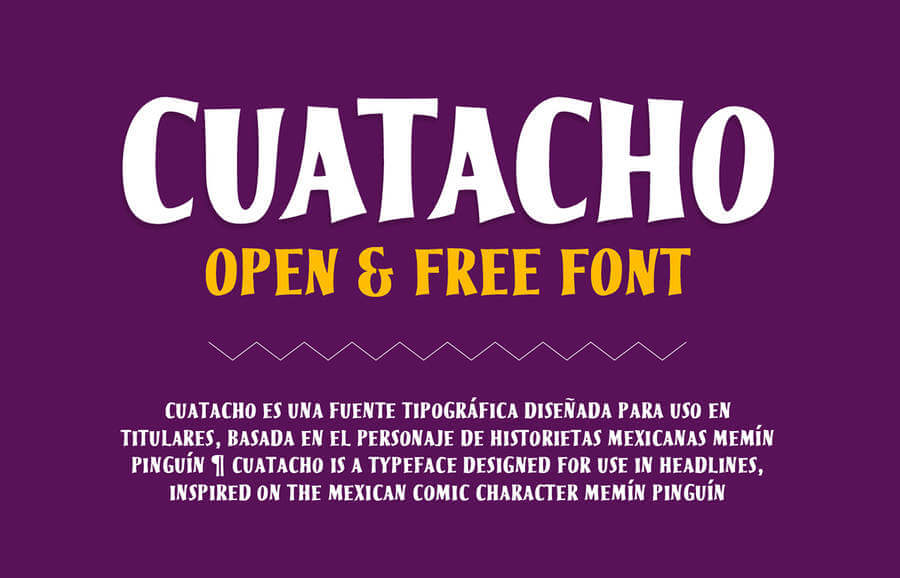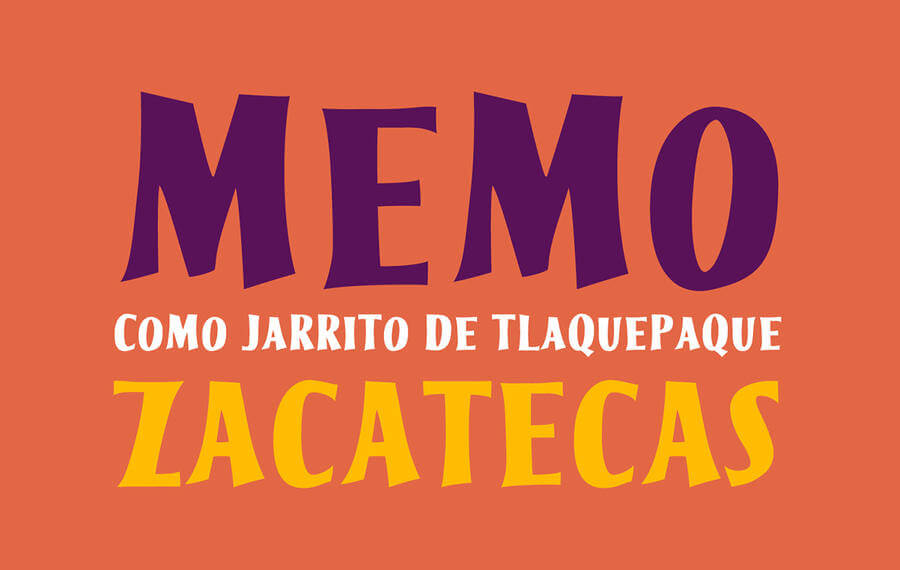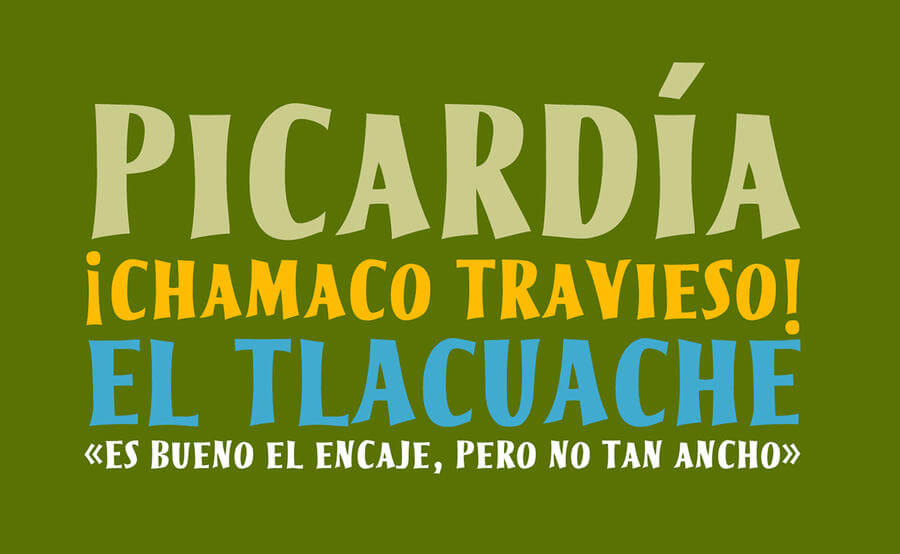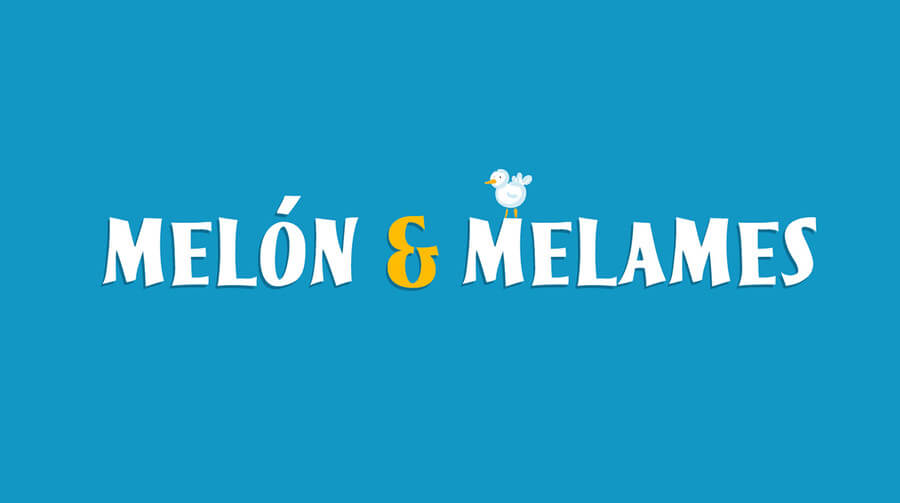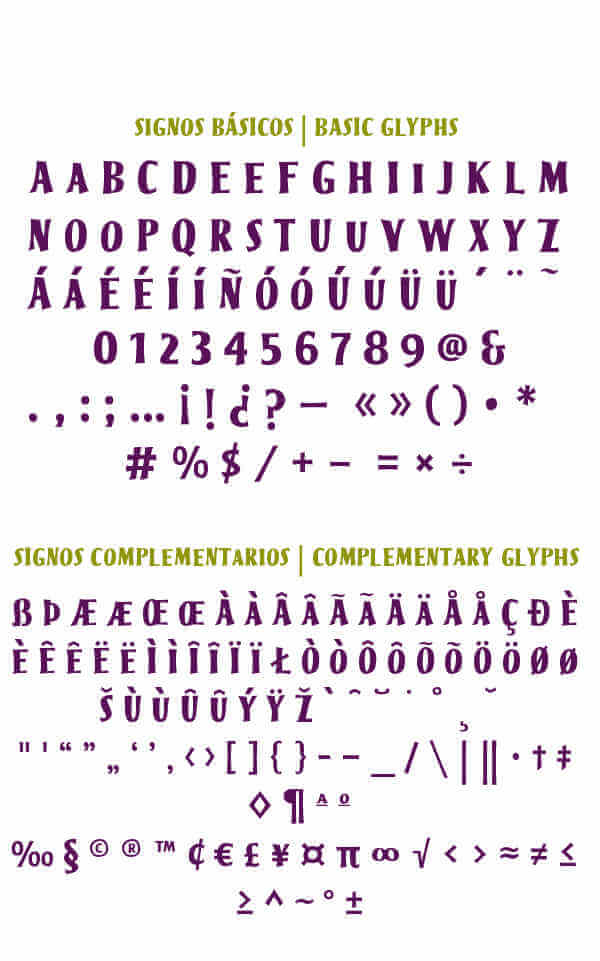
Cuatacho, es el nombre de de esta tipografía. La cual está inspirada en el personaje de historietas mexicanas: Memín Pinguín. Este personaje fue creado por Yolanda Vargas Dulché en el año 1943.
Esta fuente tipográfica fue creada a partir de la tipografía del título que aparece en todas las portadas de las historietas. En el título únicamente podemos ver cinco letras. Las cuales fueron suficientes para diseñar toda la familia, que lleva por nombre Cuatacho Typeface.
Cuatacho, fuente tipográfica basada en el personaje de historietas mexicanas: Memín Pinguín
El creador de la tipografía es Jorge Alberto Martínez. Él es un diseñador gráfico mexicano y también es un entusiasta de la letra. Actualmente, es maestro en Diseño Tipográfico del Centro de Estudios Gestalt.
Cuatacho, es una tipografía que puedes utilizar para titulares. Pero también la puedes utilizar en un texto grande. Porque aunque es una tipografía con puras letras mayúsculas. Hay dos versiones, una en donde las vocales tienen una altura menor que las consonantes.
Y la otra versión tiene todas las letras del mismo tamaño. Esa es la ideal para utilizarla en textos grandes. La familia Cuatacho está compuesta por signos básicos y muchos signos complementarios.